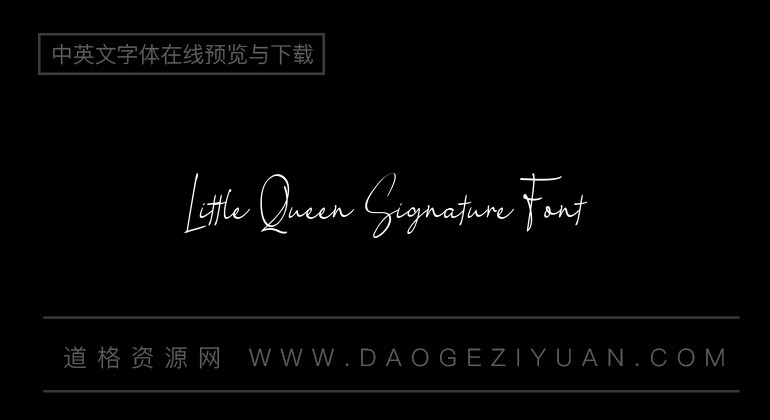
Little Queen Signature Font
Little Queen Signature Font 是一种手写风格的签名字体,其特点在于具有独特的笔画和弯曲的线条,具有艺术感和个性化。 这种字体的设计灵感来自于一位女王的签名,在字体中融入了女王的优雅和高贵,所以也被称为女王字体。它适用于个性化的品牌设计、时尚印刷品和艺术设计等场合,能够很好地传达品牌的个性和独特性。 Little Queen Signature Font 支持英文字母、数字和常见标点符号,可以在 Photoshop、Illustrator 和 InDesign 等设计软件中使用。如果你想要打造一个个性化的品牌形象,不妨考虑使用 Little Queen Signature Font。
Little Queen Signature Font是一款非常不错的手写艺术字体,具有很好的视觉感,适合于文化类的宣传设计、商业类品牌的广告和产品包装设计以及个性化文字排版等较多场景。